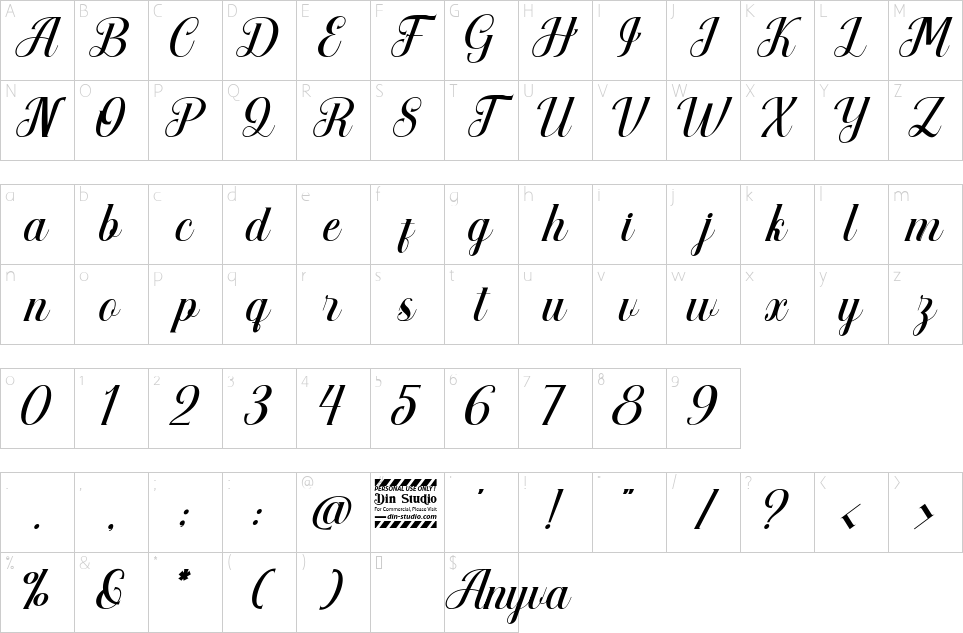
Descubra a beleza da Anyva font, uma elegante e moderna opção para personalizar seu trabalho digital. Desenvolvida pelo designer Donis Miftahudin, Anyva é uma fonte que combina simplicidade e sofisticação, perfeitamente adaptada para criar textos profissionais e design gráfico. Seja para um projeto empresarial ou para expressar sua criatividade, Anyva oferece agradáveis tipografias que adaptam-se perfeitamente tanto no Windows quanto no Mac. Com mais de 363 downloads, essa fonte gratuita é uma escolha inteligente para qualquer designer em busca de uma solução prática e de alta qualidade. Baixe já e deixe sua marca com um toque de elegância única.